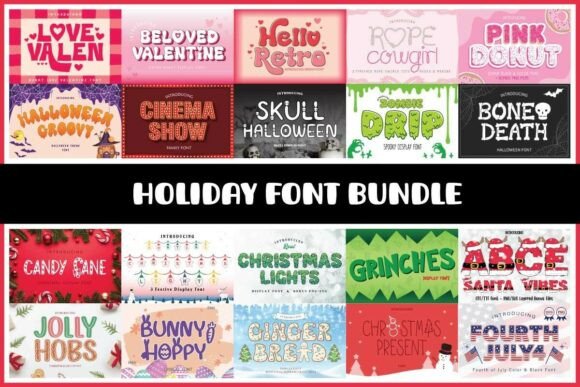
Holiday Font Bundle
Doğru tasarım öğelerini bulmak zor olabilir, ancak Holiday Font Bundle, çalışmanızı anında bir üst seviyeye taşıyan olağanüstü bir koleksiyon sunar.
İster İsteğe Bağlı Baskı (POD) ürünleri, ister düğün davetiyeleri veya sosyal medya grafikleri oluşturuyor olun, Holiday Font Bundle ideal bir uyumdur.
Uzman ipucu: Pazarda öne çıkan benzersiz, göz alıcı tasarımlar oluşturmak için bu öğeleri tamamlayıcı yazı tipleriyle birleştirin.